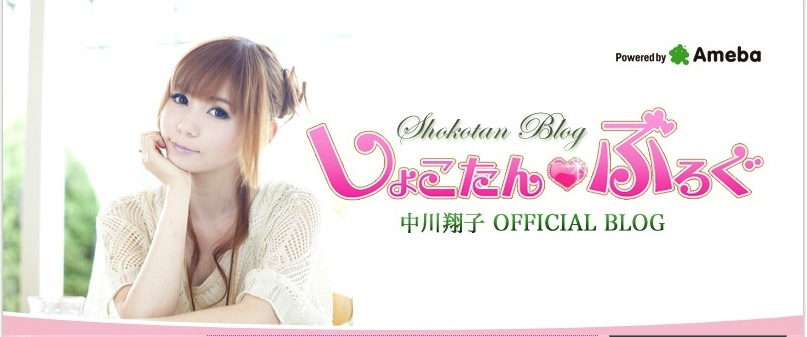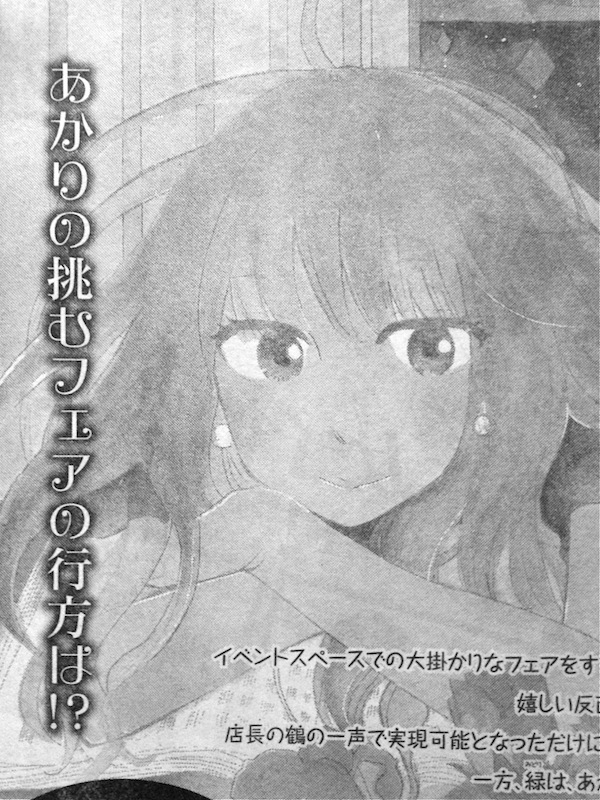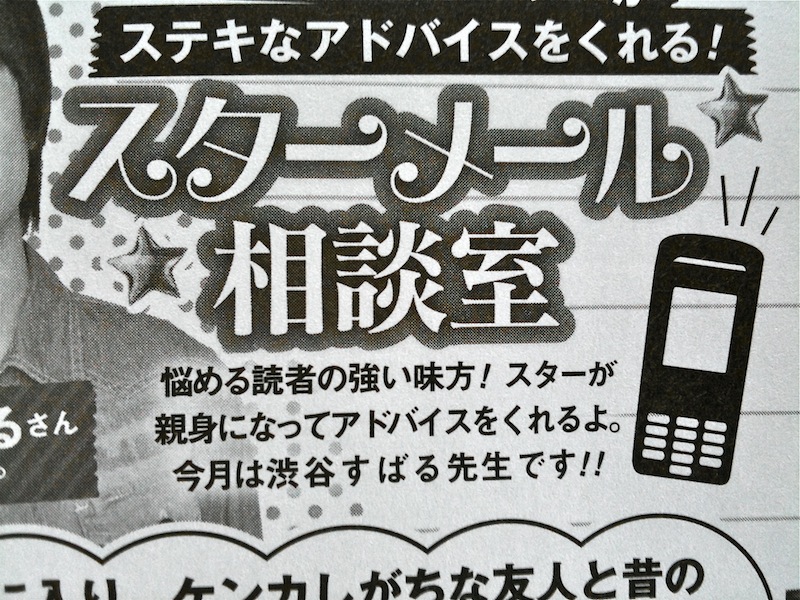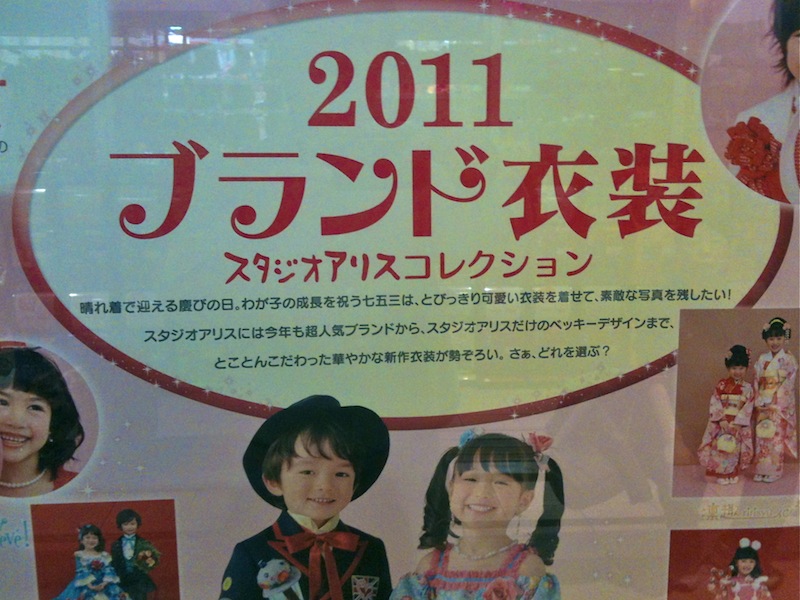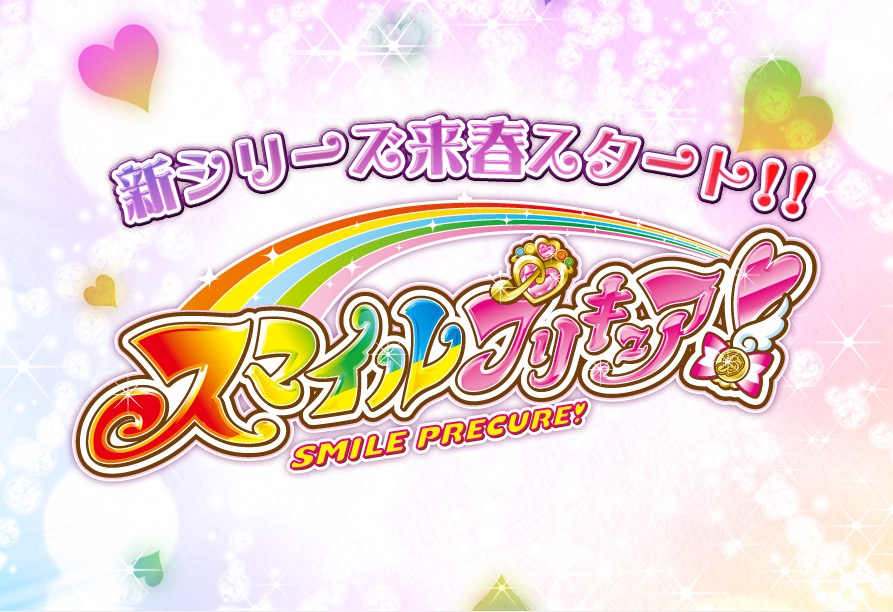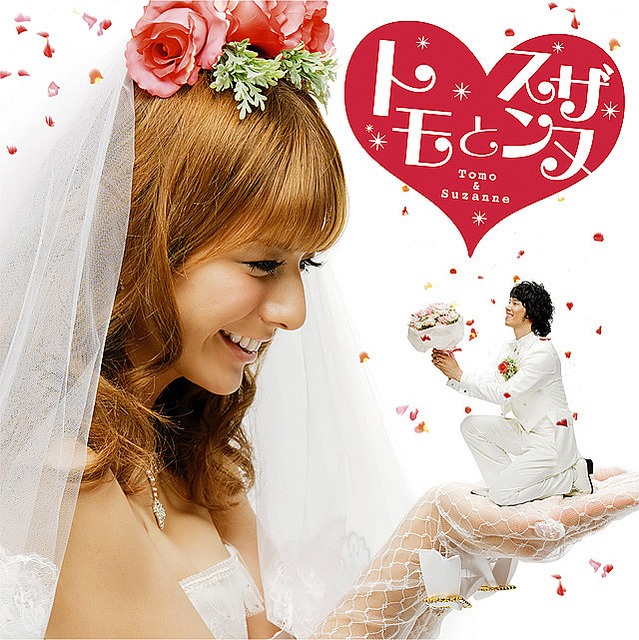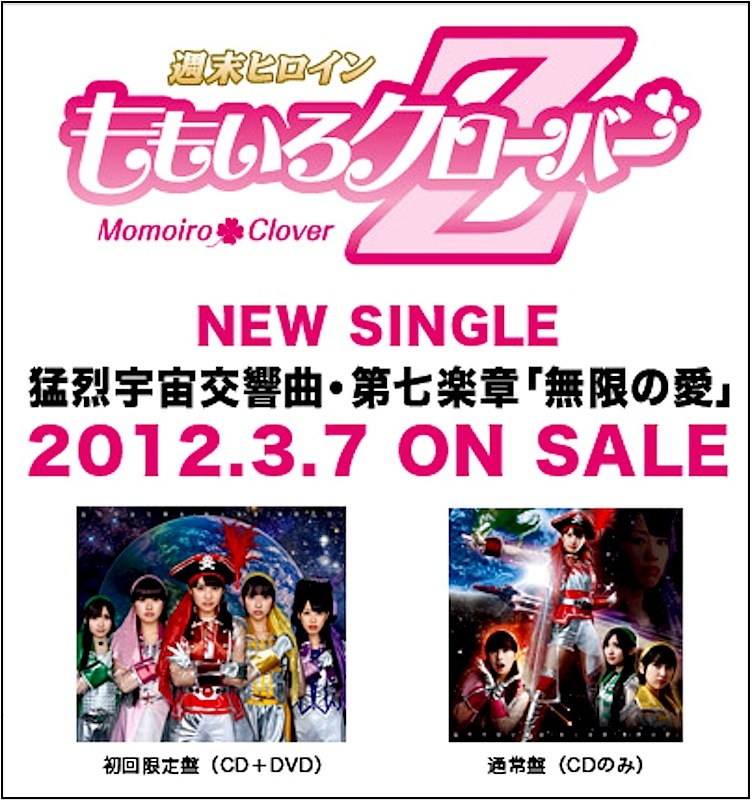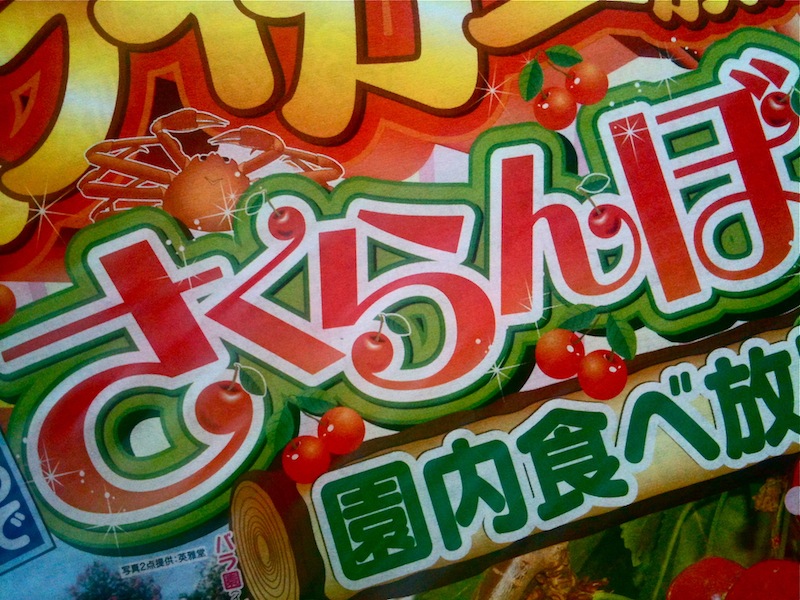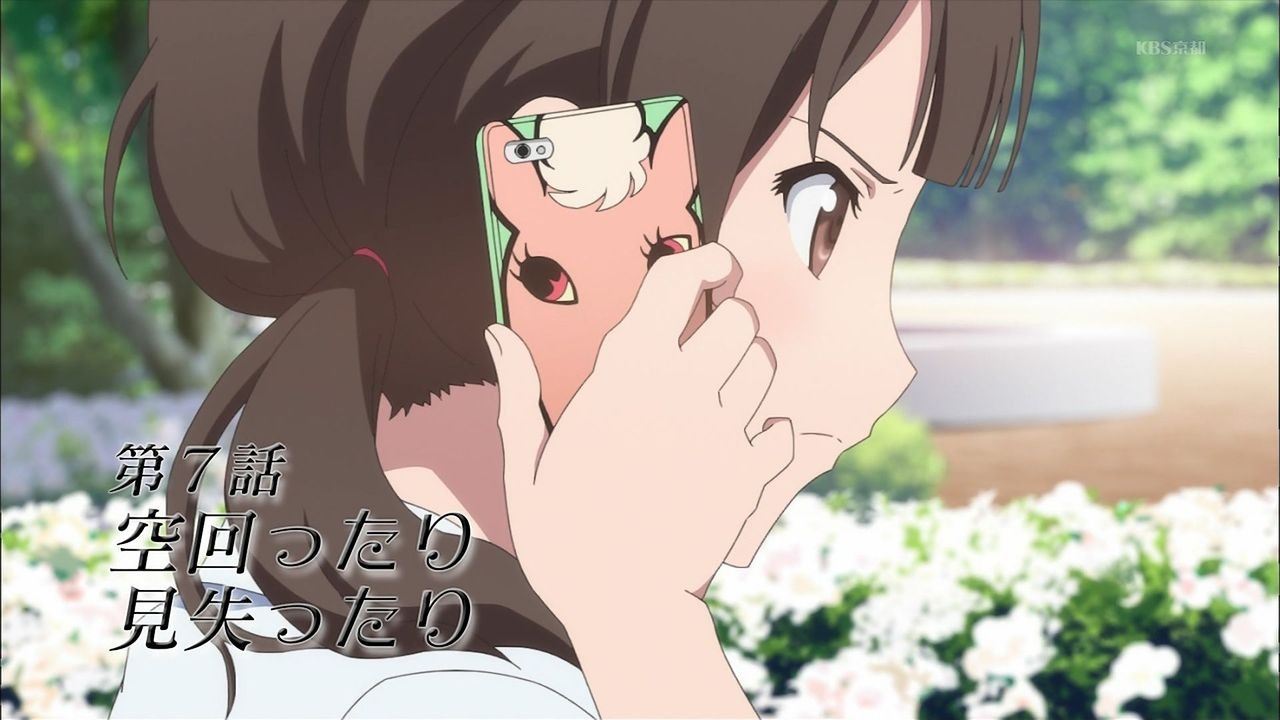
ニコニコ動画でやってる声優さんの番組のロゴに使われてました。
裏に隠れているこれですね。
NHKのニュースバラエティ  ケミカルポイント  2013年5月25日(土) 8:18
です。
WEBサイトもありました。
千住グルメマップ  さとうゆたか  2013年4月20日(土) 16:41
正式には、千住路地裏グルメマップという。
千住街の駅、シアター1010、足立区民事務所などに置かれている。
テレビ放送大学 認知心理学('13)  ケミカルポイント  2013年4月7日(日) 10:36
全部の番組をチェックしたわけではないけど、このフォントを使ってるのは上記の番組だけのようす。
ふだん私が絶対に見ない番組のようです(笑)。
このフォント、おかげさまでテレビ業界では大量に使われております。
本の表紙  さとうゆたか  2013年2月8日(金) 16:30
書名:タカラジェンヌの身体になりたい
著者:天咲千華
発行:祥伝社
本の表紙  さとうゆたか  2013年1月13日(日) 16:26
書名:あら?ジャポネ
著者:スージー伊神
発行:文芸社
女性向け漫画  さとうゆたか  2013年1月8日(火) 17:32
雑誌に付いていた別冊付録の表紙。
こちらは、雑誌の中の扉ページ。
ファミマのクリスマス  さとうゆたか  2012年12月20日(木) 20:20
ももクロを起用したキャンペーン。
こちらも。
サイト内は、えれがんと書体だらけです。
音楽CDのパッケージ  さとうゆたか  2012年12月3日(月) 15:29
ネットをウロウロしている時に発見。